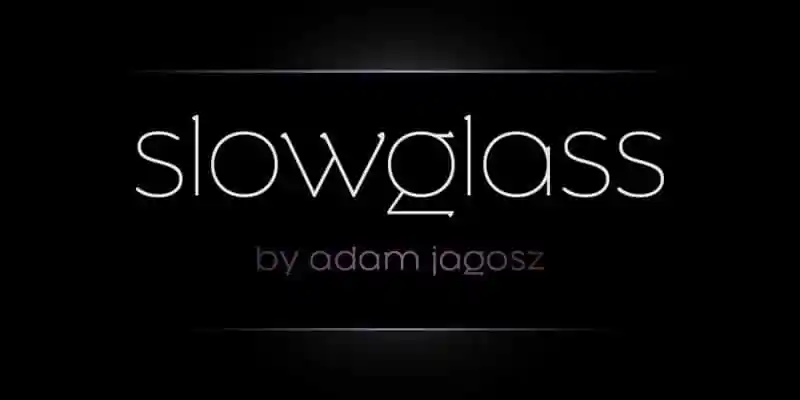
A Slowglass é uma tipografia de destaque com aparência geométrica. Inspirada nos caracteres unícuas, sua característica mais notável são os cangurus serifados que remetem a esta influência oriental antiga. Ela também tem traços ondulados suavemente, que adicionam um tom amigável ao seu design. Esta é a primeira versão desta tipografia como unicase, com o aspecto predominante sendo os caracteres minúsculos. A Slowglass apresenta uma calma e serenidade no seu design, mantendo-se distante da agressividade de outras fontes de destaque. Seu estilo leve e elegante faz dela um recurso perfeito para aplicativos que buscam uma expressão minimalista e sofisticada, seja em logotipos, sites ou materiais publicitários. Esta tipografia foi criada por Adam Jagosz, designer conhecido por desenvolver fontes cuidadosamente pensadas. A sua inspiração nos caracteres unícuas e seu design unicase tornam a Slowglass um recurso perfeito para designers que buscam uma expressão única e atemporal em seus trabalhos visuais.
Designer: Adam Jagosz